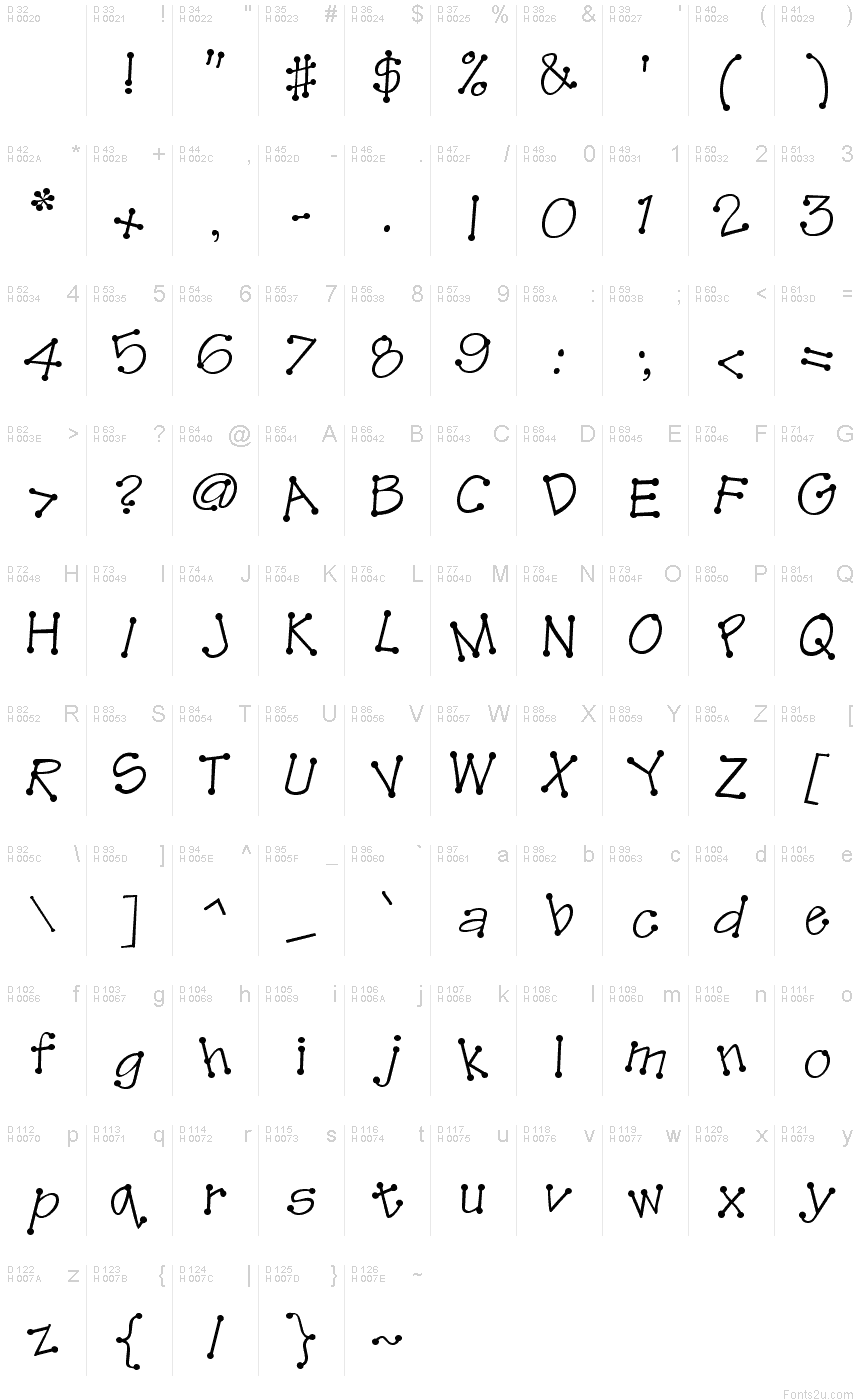
ThreadFun Italic, un font display gratuito in stile "cucito" creato da Chris MacGregor, punta tutto su un look artigianale e fatto in casa, con lettere che sembrano disegnate a filo e fissate al loro posto. Punti arrotondati, giunzioni ad anello e un ritmo leggermente irregolare conferiscono al font un tono giocoso e creativo, più vicino al ricamo o alla string art che alle comuni corsive.
È ideale per titoli di album, inviti per feste di bambini, packaging artigianali, intestazioni di blog di cucito e branding di prodotti fatti a mano, dove quelle giunzioni che sembrano nodi diventano parte del messaggio. Essendo un font gratuito, è perfetto anche per brevi titoli, segnaposti e bozzetti rapidi di loghi, quando vuoi che le lettere sembrino letteralmente cucite insieme.